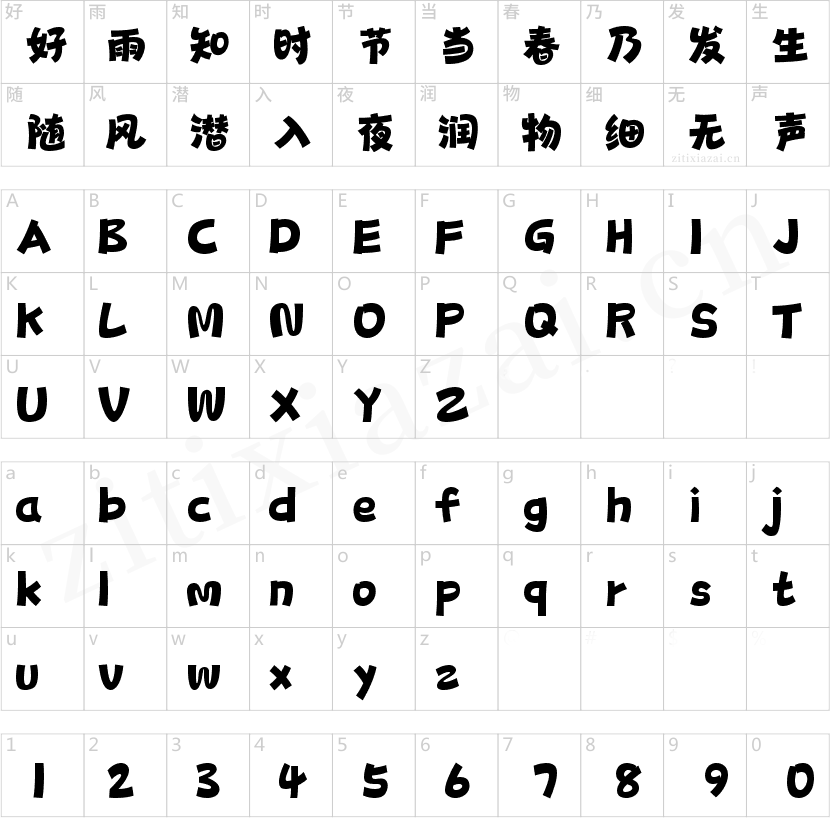
字魂269号-懒洋洋
字魂269号-懒洋洋,这款字体结构工整、笔画清晰,兼顾美观与易读性,适用于标题、正文、海报、包装、LOGO 等多种场景。字形优雅稳定,风格百搭耐看,适配日常排版与创意设计,让文字呈现更舒适、更具质感。字魂269号-懒洋洋一笔一画,皆是细节,以均衡的比例、流畅的线条打造舒适视觉体验,字形端正大气,风格简约现代。无论是商业设计、品牌宣传还是日常排版,都能轻松驾驭,让文字更有格调与力量。字魂269号-懒洋洋字体下载。
字魂字体字小魂懒洋洋字体是由字魂创意字库设计并生产的一款可商用的字体,被收录于字小魂系列。该字体支持GB-2312标准以及最新的字魂ZH7144标准,包含7144个中文、字母、符号和数字,字体类型偏向黑体,具有活泼、动漫、可爱的风格,在市面上广泛用于游戏动漫、媒体&H5、游戏等场景。